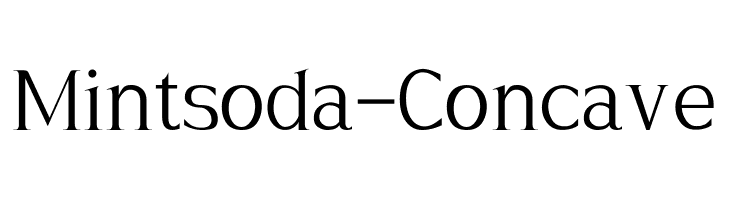
A playful, handwritten font with tall, narrow letters and a casual, whimsical style.
A bold, italicized font with a gradient effect, perfect for modern and dynamic designs.
A bold, textured slab serif font with a vintage shadow effect.
A classic cursive font with elegant, flowing lines and consistent stroke thickness.
A tall, narrow serif font with a blend of classic and modern elements.
A whimsical font featuring cartoon mice interacting with bold, outlined letters.
A bold, distressed font with a vintage, hand-printed appearance.
A modern, bold, and italicized pattern of stylized letters.
A playful and whimsical font with decorative elements and unique embellishments.
A playful, handwritten font with rounded, whimsical characters.
A modern, clean sans-serif font with excellent readability.
A bold, geometric font with playful, rounded characters.
A playful, rounded font with bold, bubble-like characters and thick outlines.
A playful, rounded font with a bold and whimsical style.
A bold, distressed serif font with a grunge aesthetic.
A playful, hand-drawn font with a rough, textured appearance and whimsical style.
A bold, rounded font with a modern and playful style.
A bold, dynamic font with a playful, distorted style.
An elegant, flowing script font with modern flourishes.
A playful, handwritten font with a modern, energetic style.
A bold, graffiti-inspired handwritten font with dynamic strokes.
An artistic, hand-drawn font with intricate, sketch-like details.
A bold, italicized font with a dynamic striped pattern and high contrast.
An elegant italic font with flowing, cursive strokes and a moderate slant.
An ornate, medieval-style font with intricate flourishes and Gothic influences.
A dynamic and elegant script font with fluid, cursive letterforms.